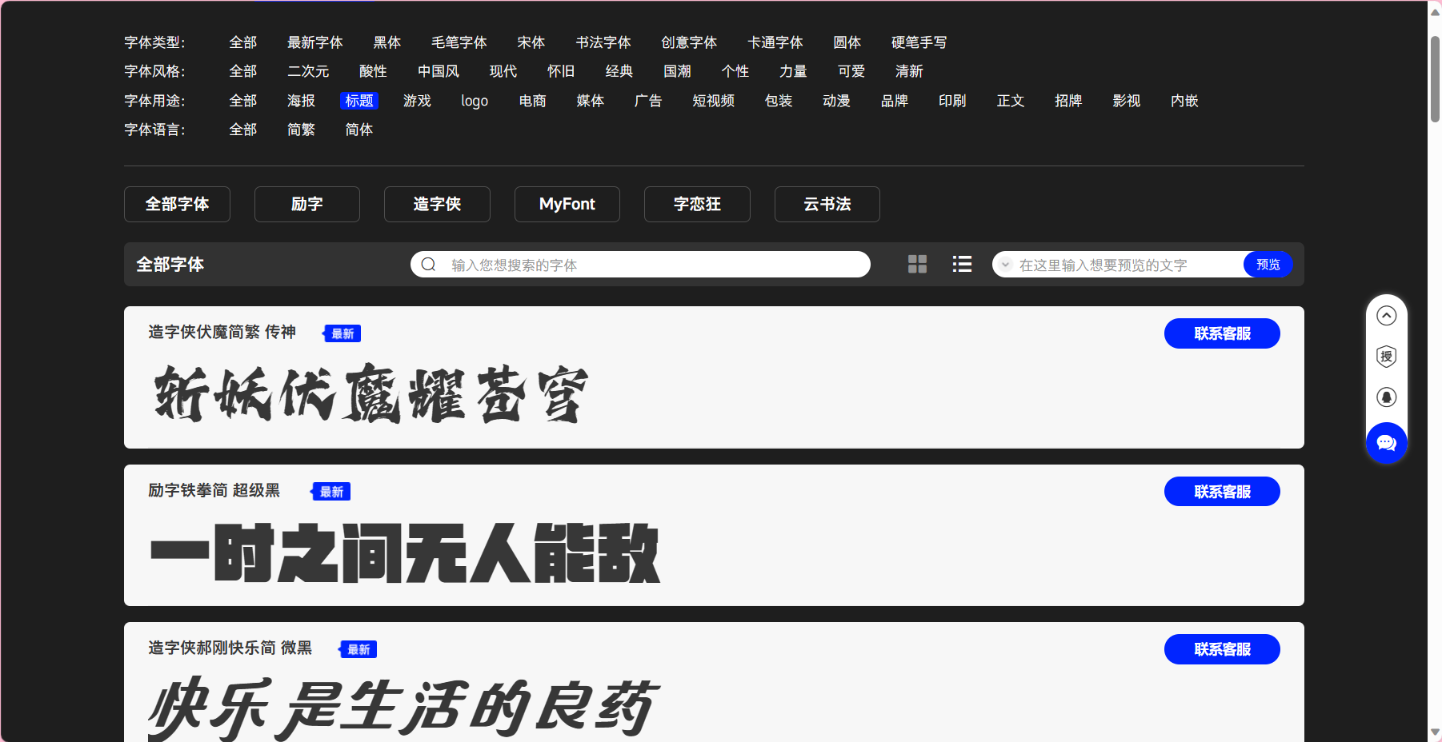
电商用字须知 | 如何选择电商节的吸睛标题字?
双11、双12 电商节马上要到了,很多品牌有直播很、促销、包装等字体场景需求,却不知道如何找到更合适的字体,励字造梦共创字库整理了几款精选标题字!
笔墨浓厚,粗细对比较为明显,字体结构较为中正,字体里笔画的“勾、提、挑、捺”等笔画特点明显、夸张,极具视觉冲击力,单字结构收放自如。
一款创意黑体字,笔画粗壮、字面宽大,饱满的块面感以及折角圆设计,视觉冲击强烈,犹如铁拳出击,横扫千军。